去年,为迎接建国70周年,市少年宫举办少儿书法大赛,10岁的小孙子一举拿了个一等奖,全家人都很高兴,可偏偏小傢伙却高兴不起来。一问,才知道是一起的小朋友笑他只会写“颜体”,不会写“尚巍体”。
其后,快到春节的时候,社区举行隆重的表彰先进大会,宽阔喜庆的主席台背后大屏幕上,赫然用“尚巍体”打出“某某社区迎春表彰大会”。
猛然间,我感觉到这“尚巍体”几乎是无处不在,广告、店招、影视海报和电视荧屏,处处都可见其身影。曾有一书法媒体对网络滥用此类“字库书法”提出过意见(注1),直截了当把“尚巍体”列入了“江湖书法”;《人民日报》也曾以“还字库一片净土”为题(注2),对此类“字库书法”提出了批评,然而却遭到了广告及美术设计人士的猛烈反击。他们认为字库书法,无论是“尚巍体”还是其他字库书体,不过是运用书法元素进行的美术字创作,是艺术设计范畴,与书法无关。
艺术设计人士的此类做法和观点, 不能不让人对书法的生存,生出一丝忧虑……
书法,是我们民族文化的瑰宝,也是我们民族文化的基因。在中华文明发展的进程中,书法之所以成为艺苑的一朵奇葩,并影响着日韩等国的文化,并不仅仅因为汉字是象形文字,而更重要的是其笔墨点划具有丰富的表现力和千姿百态的形体美。书法作为中国文化的象征,体现的是一种东方美学理念。
过去,在书法作为文化人的基本特征时代,每一个读书写字的人,都是书法艺术的创造者和欣赏者。写得赏心悦目的,称之为书法很好,写得潦草杂乱的,称之为书法很差。
如今,随着中国经济的崛起,学习中文,识写汉字,运用汉字及线条点划的丰富,设计引人注目的商业logo,已成为世界性文化现象。
“悦目”、“赏心”,以及从传统书写汉字的笔墨线条中,注入和体验情感表达,并感受视觉美。这才是书法成为其独立艺术的真正原因和魅力之所在。
然而,在上世纪“钢笔文化”取代“毛笔文化”的潮流下,以毛笔为主要工具的传统书法日益走下坡路。钢笔PK毛笔,经过了差不多整整一百年的较量,传统书法终因网络的普及,彻底退出了个人日常书写的应用领域。为此,文化学者余秋雨先生,写了著名散文《笔墨祭》,似乎已为中国书法作了一篇虽不是肝肠寸断,但却令人惆怅不已的祭文。当然,余先生在文末也留了个尾巴,说是书法作为艺术还是应当存在并发扬下去的,但也不过是作为现代“喧嚣社会的审美抚慰”。余先生的成名之作《文化苦旅》,其封面题字就是他自己的毛笔书法墨迹。我想,这也许是余先生给书法留下的一块墓地吧?
秉承余先生的高论,面对书法的衰落,如今的书法家大多认为,书法是艺术,普通人提起毛笔写出的汉字,不是书法,只是写字。原以为这类观点只不过是书法界面对键盘文化的离殇咏叹,但仔细斟酌,似更有“曲高和寡”之意。如玩射墨书法的邵岩先生就认为,老百姓根本就不懂书法艺术,也不懂“射墨”书法创新。在当今书法界不少人看来,书法是艺术、是国粹,况且书画同源,所以,就应该和国画一样登堂入室,建立专业,聘请教授,设立学位;就应该和国画油画一样搞大赛,办展览,出专集,出馆藏作品;就应该在苏富比等书画拍卖市场举拍锤、论平尺,计价各位书法大咖作品……
“我的柔情你永远不懂”,书法这个千百年来谱写中华文明的农家美女,似乎转眼间已变成远在天边有着霓裳艳影的嫦娥姐姐了。只有在春节这样的良辰时节,书法家们在“文化下乡”的政治感召下,才能如过往一样下凡人间,为民众写下大同小异的门楣春联。自然,大多数书法家不会认为写春联是艺术创作,苏富比拍卖市场似乎也不拍卖现代书法家的春联。下乡为民众写春联,更像是一场文化走秀。
然而,艺术设计(字库字法)界却报之以“你的柔情我永远不想懂”。他们认为,能洗眼吸睛吸取流量就是硬核;既然书法的日常书写实用功能已然全废,而汉字的天然视觉美感,以及书法浓淡枯润点线变化的应用性却丝毫未减,利用书法的这些特点设计制作商业logo,引人注目的效果较之传统的只有平直线条的宋体黑体美术字,或更能彰显其特立独行的设计个性。于是,随着键盘文化的普及,在艺术设计及广告设计领域,大量违背书法规律和美感的“字库书法”,如当今流行的“尚巍体”、“卫禹体”,等等,就应运而生了。
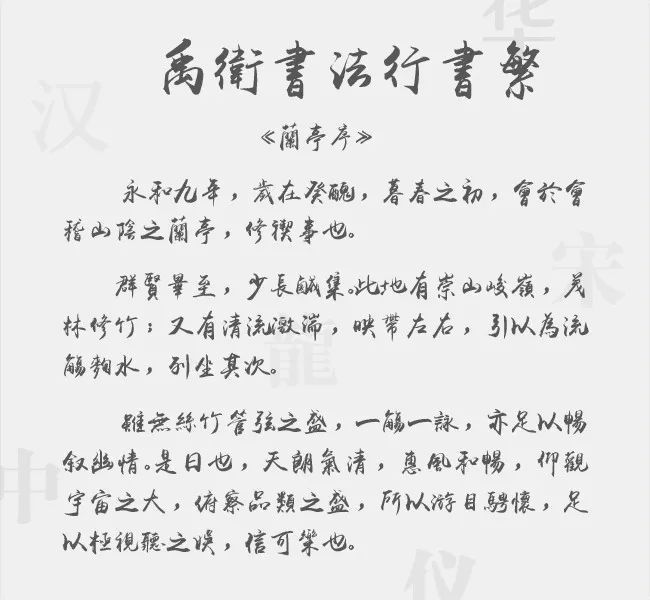
最初,这些违背书法规律和美学原则的“字库书法”只是在比较狭窄的广告设计领域中出现,并不像印刷字体那样广为人知,所以并未引起人们太多关注。但其后由于网络搜索与儲存功能的完备,这些“字库书法”就堂而皇之进入了字库,其传播和泛滥犹如失控的“外来物种”,恣意滋生蔓延,充斥着人们的视觉,影响着人们对书法的审美意识和欣赏水平。
改革开放之前,文化界曾经流行一个公式化口号:对于文化阵地,“如果A不去占领,那么B就必然会去占领”。套用在如今网络文化传播领域,同样是这个道理:你说“尚巍体”、“禹卫体”不是书法,或者说是违背书法规律的“江湖书法”,那为什么网络影视作品,广告作品都喜欢用这些字体呢?你说人家占领了字库,那你们这些书法家怎么又不去占领呢?
这,的确是一个令人深思的文化传播现象。
“尚巍体”等字库书法以免费姿态跻身于字库,实际上是利用汉字的大众文化特点,在市场上为其推广应用,选择了一条平民路线。当其得到市场认可,人们大量使用之后,则身价倍增,光芒自显。这就网络时代的特点。想当年微信未推出之前,手机用户相互间发条彩信,还得收费,而微信一露面即以免费的姿态迅速占领市场,如今又还有几个人去用彩信呢?
当然,字库书法的泛滥也有一个“破窗效应”问题。字库书法应用既然无需成本,取用方便,吸引眼球,在网络的推动下,必然强化社会上对字库字体的大量应用,并带动其他书写设计者极尽扭曲变态的制作字库书法,从而呈现出一种“恶搞汉字”的现象。
而书法家的字体要入字库,首先从书法家方面来说就有以下担心:
第一,以什么字体入字库?长于正楷、隶书和行书的好说,但又担心没有了自己独立的风格,因为书法家作品的艺术特征,并不完全是单字就能表现的;
第二,书法家作品入字库,是否存在着“自降身价”的危险?会不会像滥市的白菜价一样掉价呢?如某书法家现书画市场价已达万元一平尺,进入字库后,每一个字怎么样计价,今后书画市场又还能不能达到万元一平尺的价格呢?这是书法家本人及市场都无不担心的问题;
第三,书法家字体字形的知识产权怎么来维护?有人模仿、克隆,又当如何维权呢?
这一系列问题,无不困扰着书法家作品进入字库。于是,书法家和艺术设计师也只好各自恪守着“你走你的阳关道,我过我的独木桥”。字库书法便以其大众性和更符合商业需求滥殇于市,其结果是民众的书法欣赏水平和审美意识大幅度下降,文化传播领域充斥着与书法美学格格不入的书体。
书法,是老祖宗留给我们的遗产,它之所以成其为艺术,实在是源于汉字的象形会意具有强烈的视觉冲击效果。如果把其他拼音文字看作是以音律和听觉取胜的艺术,那么汉语言文字就是以形象和视觉取胜的艺术。书法个人日常书写的实用功能虽已不在,但书法在文化传播领域的应用功能却是空前的增强了。人们学习、模仿名家书法,从而形成其自身的审美欣赏意识,已不再是单靠执笔临帖,而更多的是通过网络及媒体的示范来形成,谁占领了网络和媒体,谁就占领了文化传播及审美的制高点。
书法,不论说得多么高贵、神圣抑或神秘,不管说它是写字还是艺术,它始终就是一个以汉字识写为基础的大众文化和大众艺术。网络影视及广告书法,就是当今普通民众接触、学习和欣赏书法最直接最简单的方式。
如果文化界、书法界能够让书法回归其大众化的本来面目,顺应人们因网络而带来的视觉空间扩张的应用需求,那么,书法或将向死而生;否则,我们只有拜托艺术设计界:
请给老祖宗的书法遗产留一块墓地!